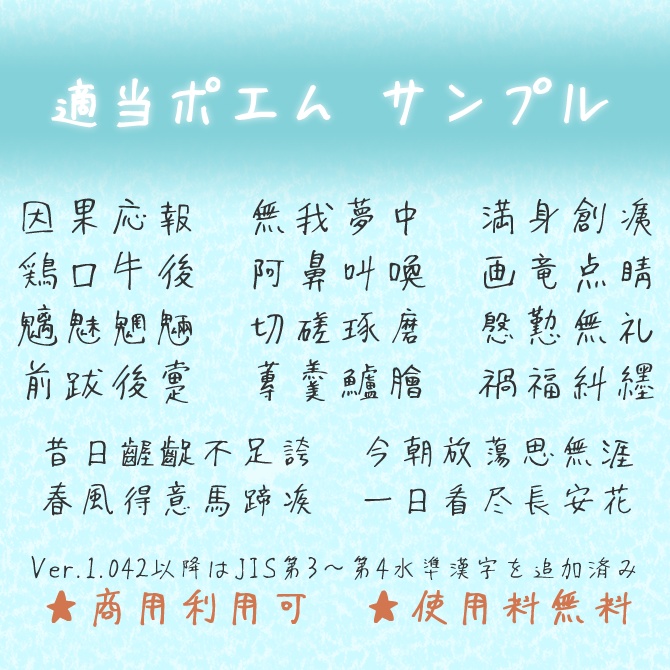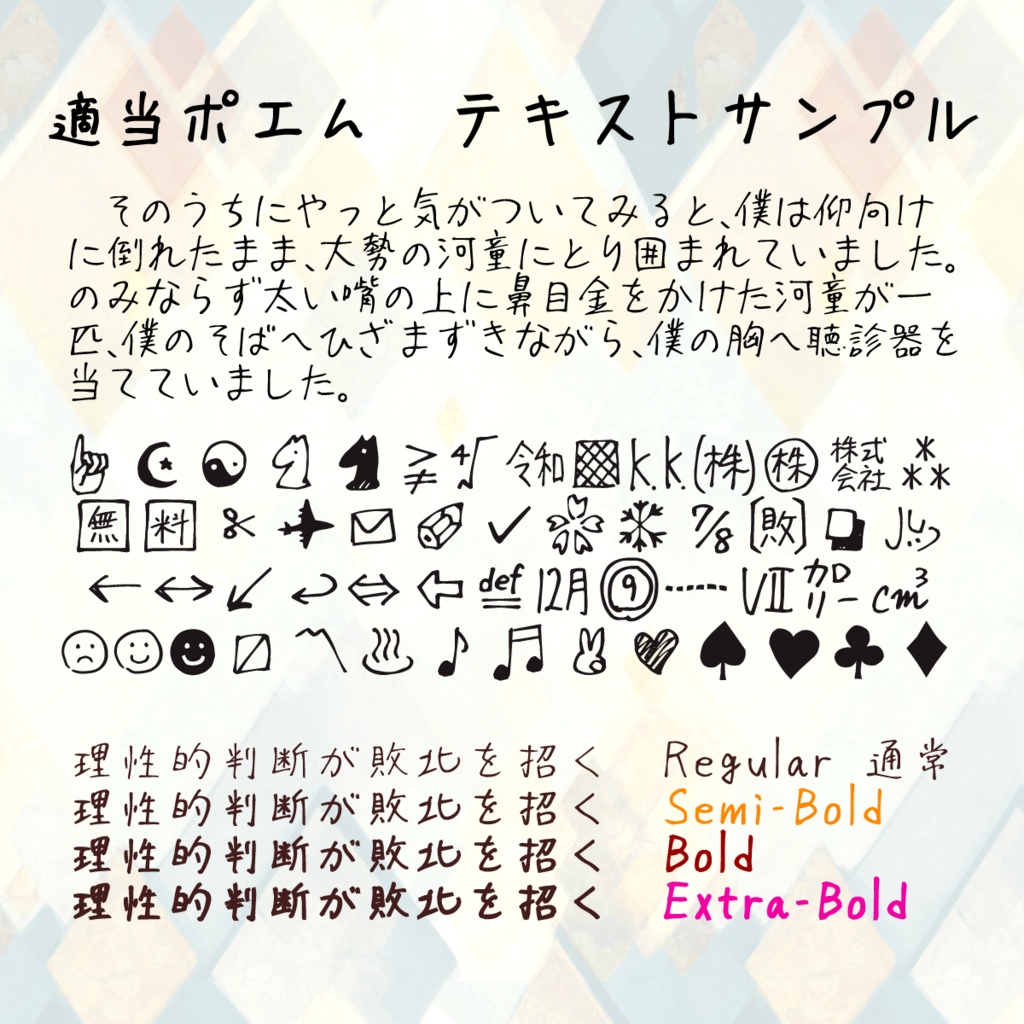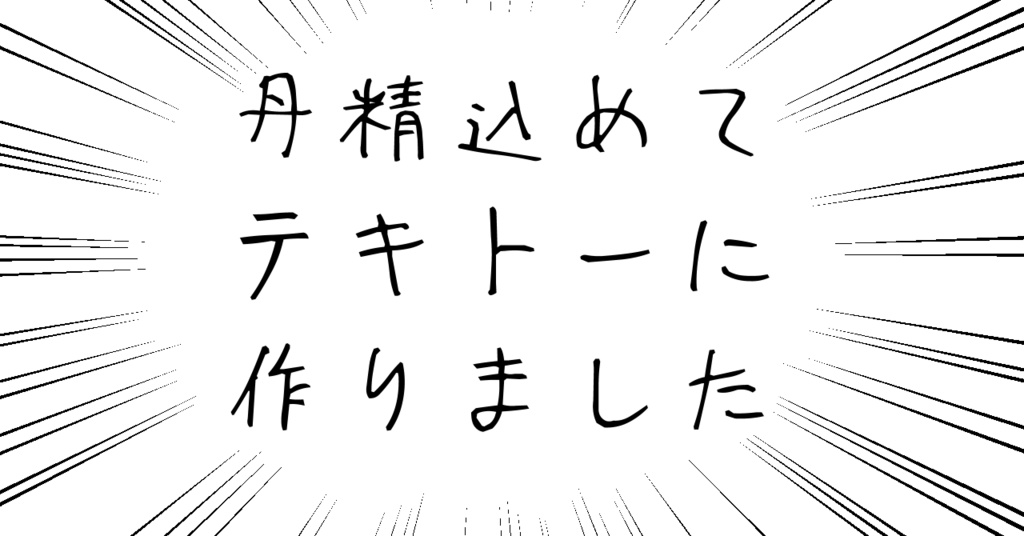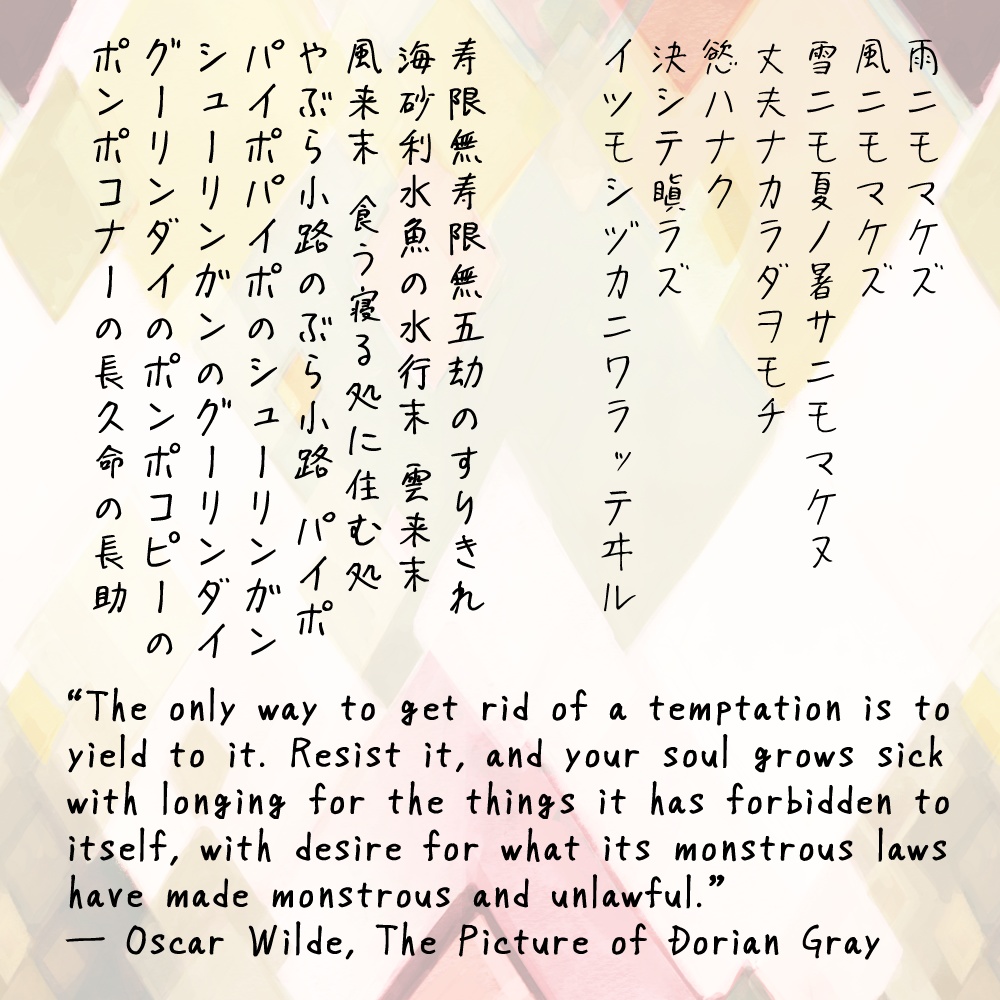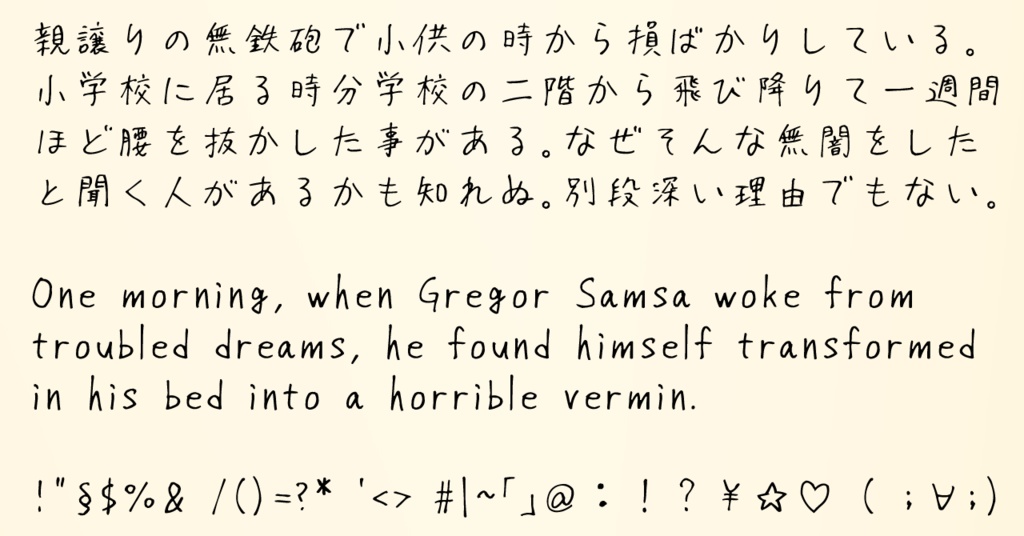
適当ポエム(フリーフォント)
手書きの日本語フォントです。 英数字、ひらがな、カタカナ、JIS第1~4水準漢字、その他の漢字や記号など、約16100字を収録しています。 ゲーム、イラスト、動画、印刷物など、さまざまな用途に使えます。 文字の大きさや丁寧さにばらつきがあります。 アップデートにより文字追加や誤字修正、微調整を行っています。
TekitouPoem.ttf が通常版です。 太さが違うバージョンを作ってみました。中太(Semi-Bold)、太字(Bold)、特太(Extra-Bold)です。機械的に太くしただけなので、細かい字は潰れます。ご了承ください。